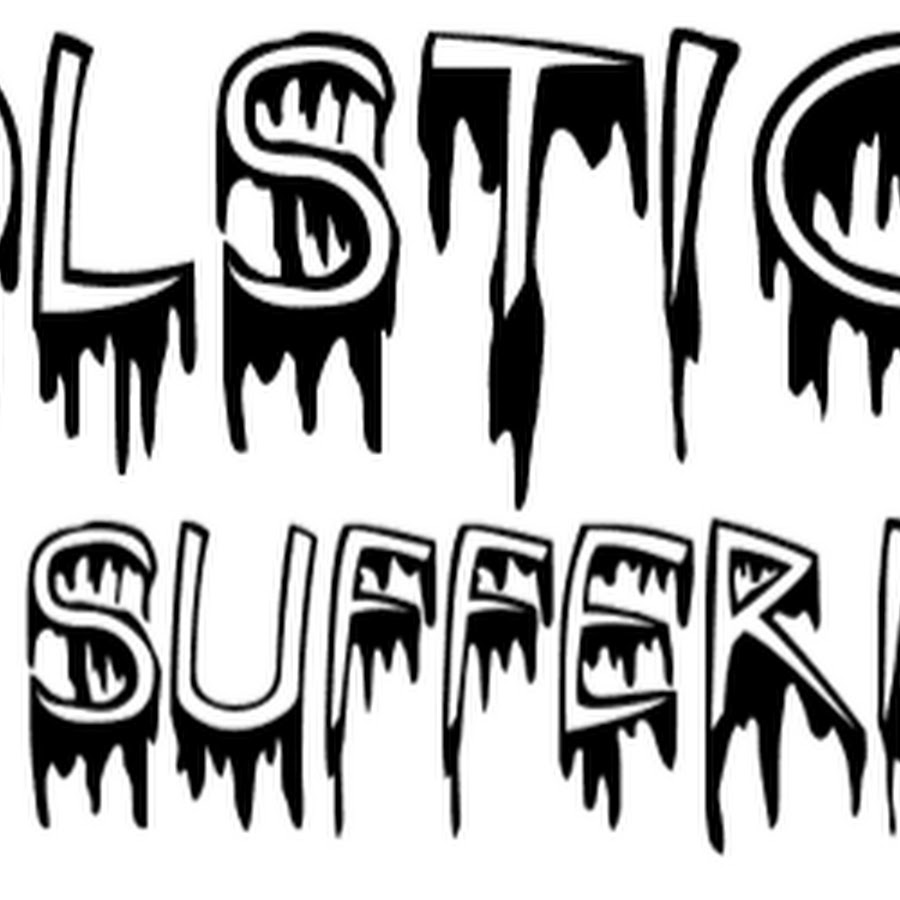
Шрифт с потеками: Бесплатные шрифты-кисти
подойдёт для Хэллоуина.
Шрифт Cold Night for Alligators
Жирный шрифт Feast of Flesh BB
Тонкий неравномерный шрифт Nightmare
Обведенный шрифт Brutal Tooth
Рваный шрифт Creepsville
Жирный обведенный шрифт Friday 13
Шрифт с потертостями Survival Horror
Готический шрифт
Шрифт кистью Mars Attacks
Тонкий готический шрифт Horror
Шрифт с элементами иллюстрации Holitter Spike
Шрифт с брызгами краски DBE-Beryllium
Грязный прописной шрифт The haine au carre
Затертый грязный шрифт Cannibal Corpse
Иллюстрированный шрифт Solstice Of Suffering
Шрифт с черепами Zombified
Шрифт в стиле Хэллоуина Kreepshow Frigid
Неаккуратный шрифт с потеками HoMicIDE EFfeCt
Кровавый шрифт
Угловатый шрифт с потеками Brain Damage
Иллюстрированный шрифты в точечку The Blob
Жирный шрифт с потеками краски Plasma Drip Font
Шрифт с пробелами Were Wolf Font
Гранж шрифт You Murderer Font
Необычный шрифт Creepygirl
Симпатичный шрифт Spookymagic
Хэллоуин шрифт Hello ween font
Битый шрифт Black Oak
Аккуратный готический шрифт Resident Evil
Шрифт с элементами веток деревьев Wild Wood
Неровный шрифт Sin of the innoccent
Стилизованный шрифт Windswept MF
Устрашающий шрифт 13th Ghostwrite
Потекший шрифт Splywaj
Кровавый шрифт Almost Dead Bloody
Адский шрифт GhostParty
Шрифт с завитками Bosque Encantado
Шрифт в виде косточек 4 Dogs
Стильный шрифт BN Manson Nights
Шрифт в готическом стиле Amhole
Шрифт с узорами Vtks espinhuda
Прописной шрифт Gantz
Шрифт от руки Last N Line
Готический шрифт Carsi
Обведенный шрифт Dzr Mental
Шрифт в виде набросков Psychotic
Размазанный шрифт Convalescence
Шрифт с потертостями и потеками Cocaine Sans
Почерканный шрифт Knife Fight
Грязный шрифт с пробелами Blasphemy
Жирный грязный шрифт El&font Block